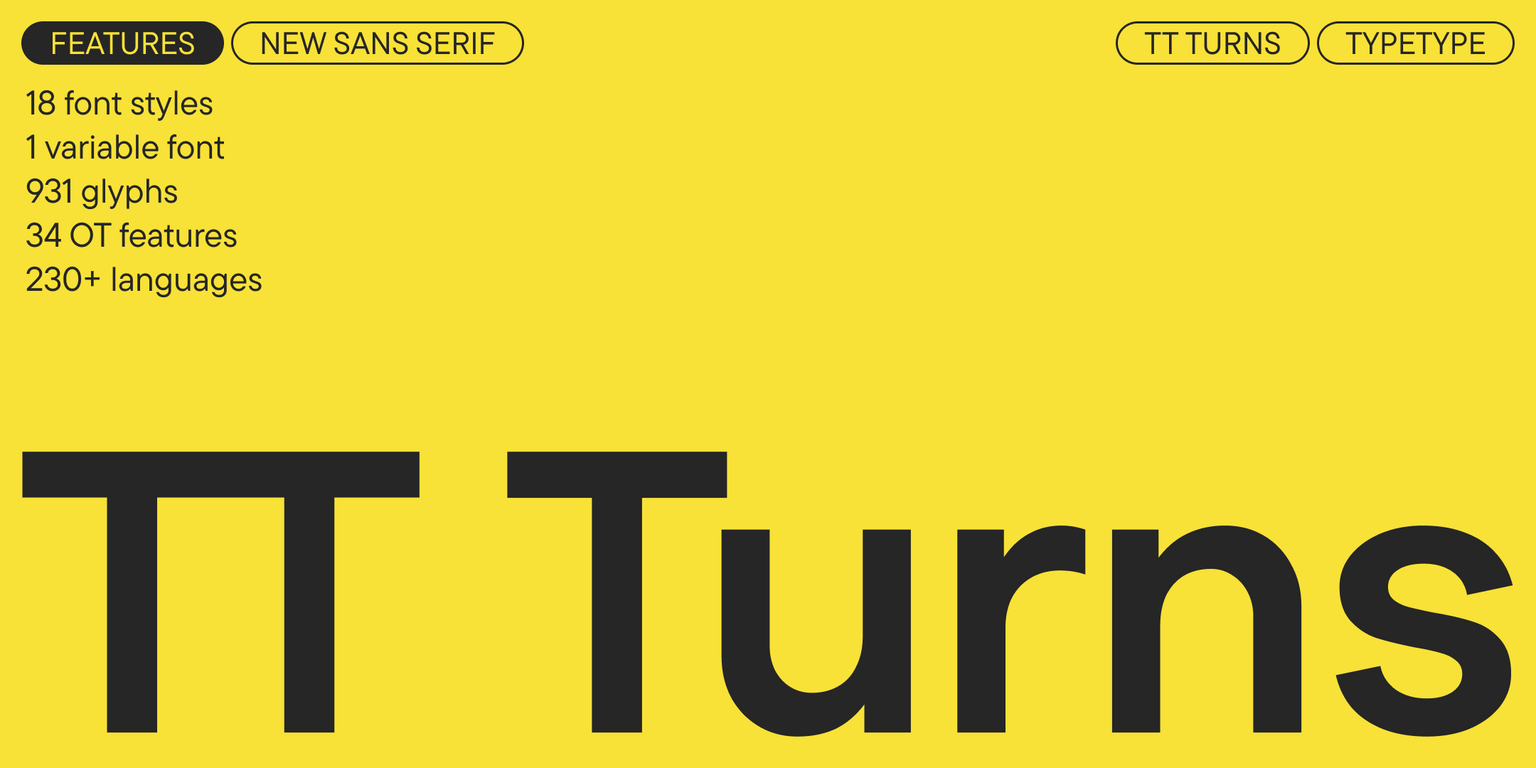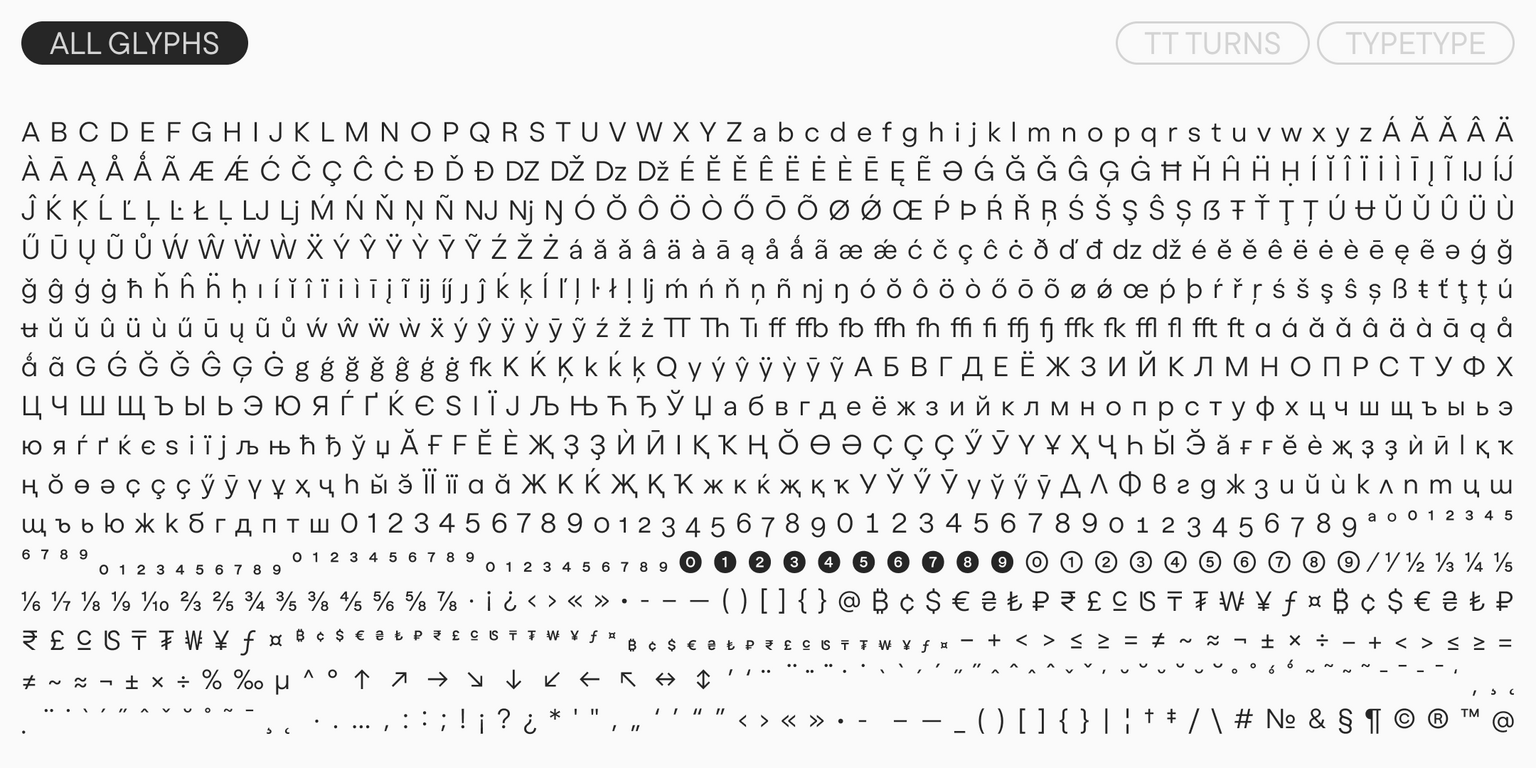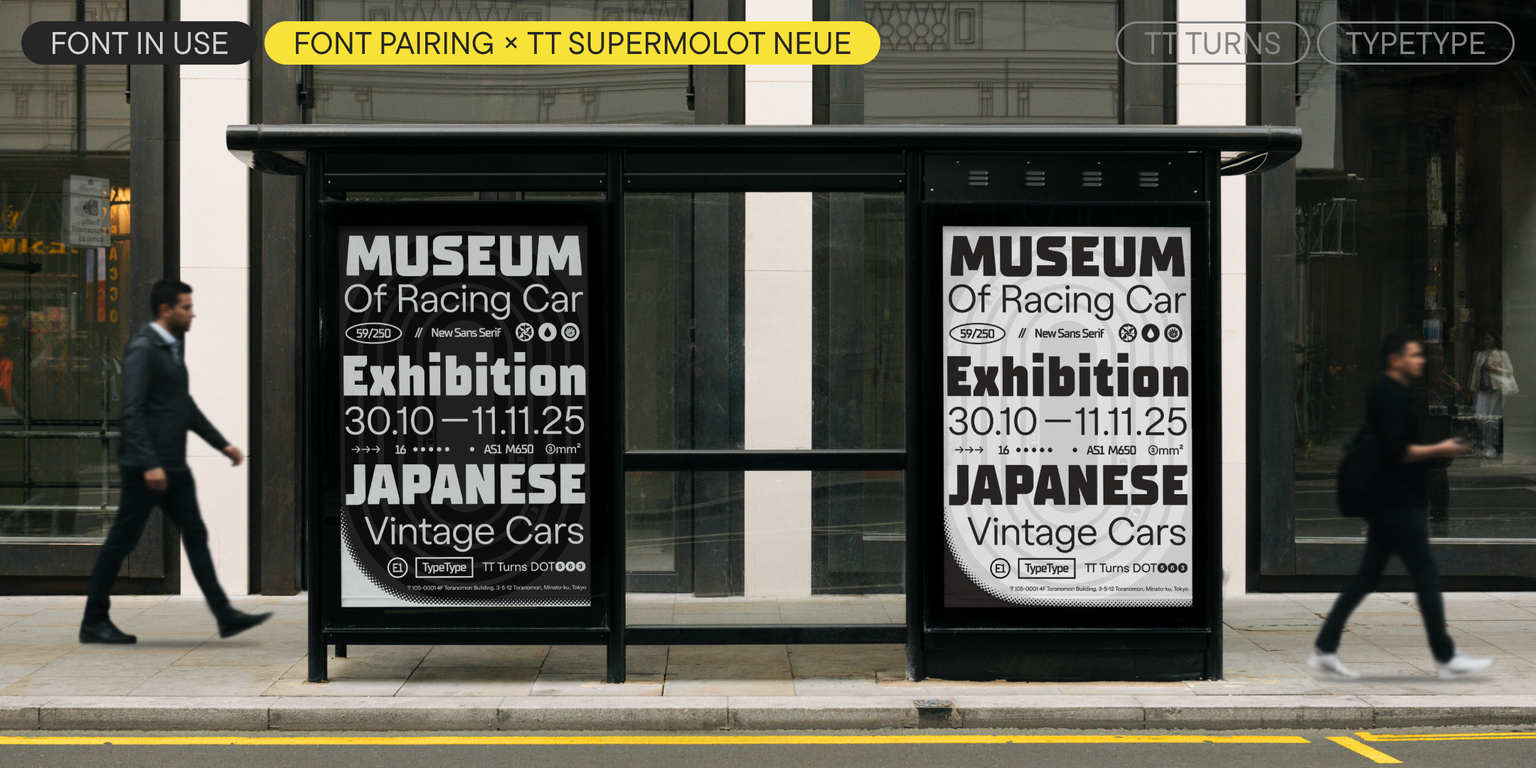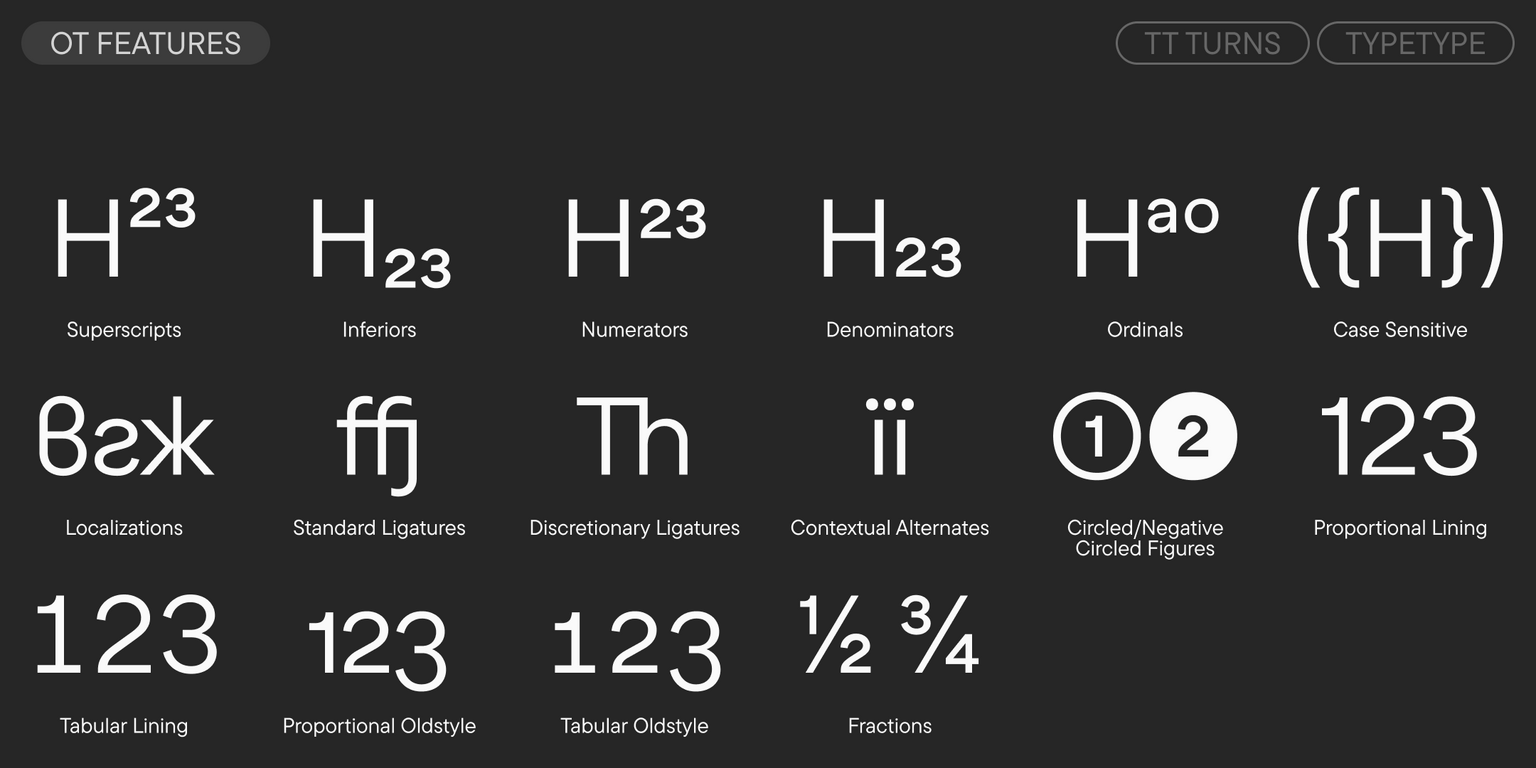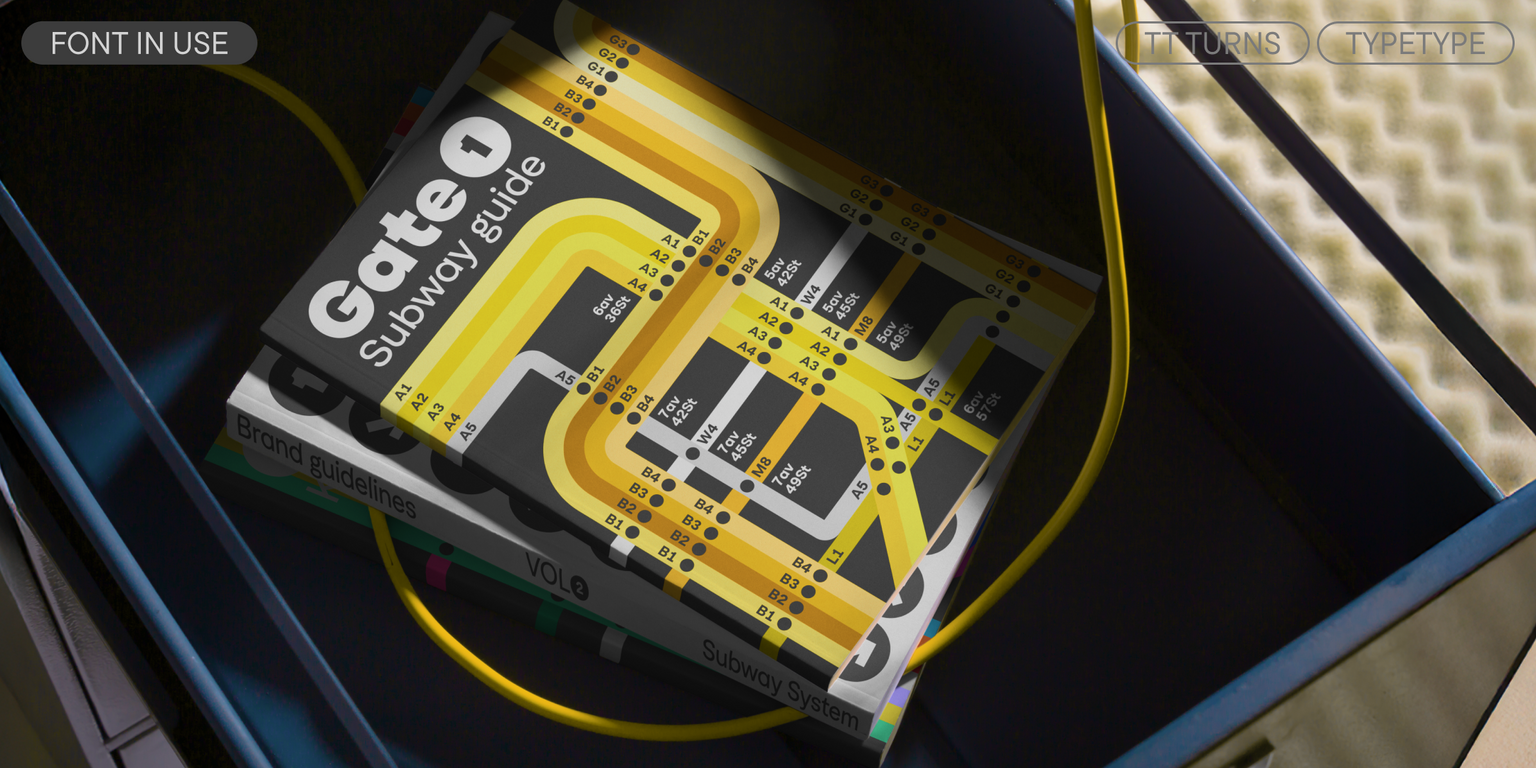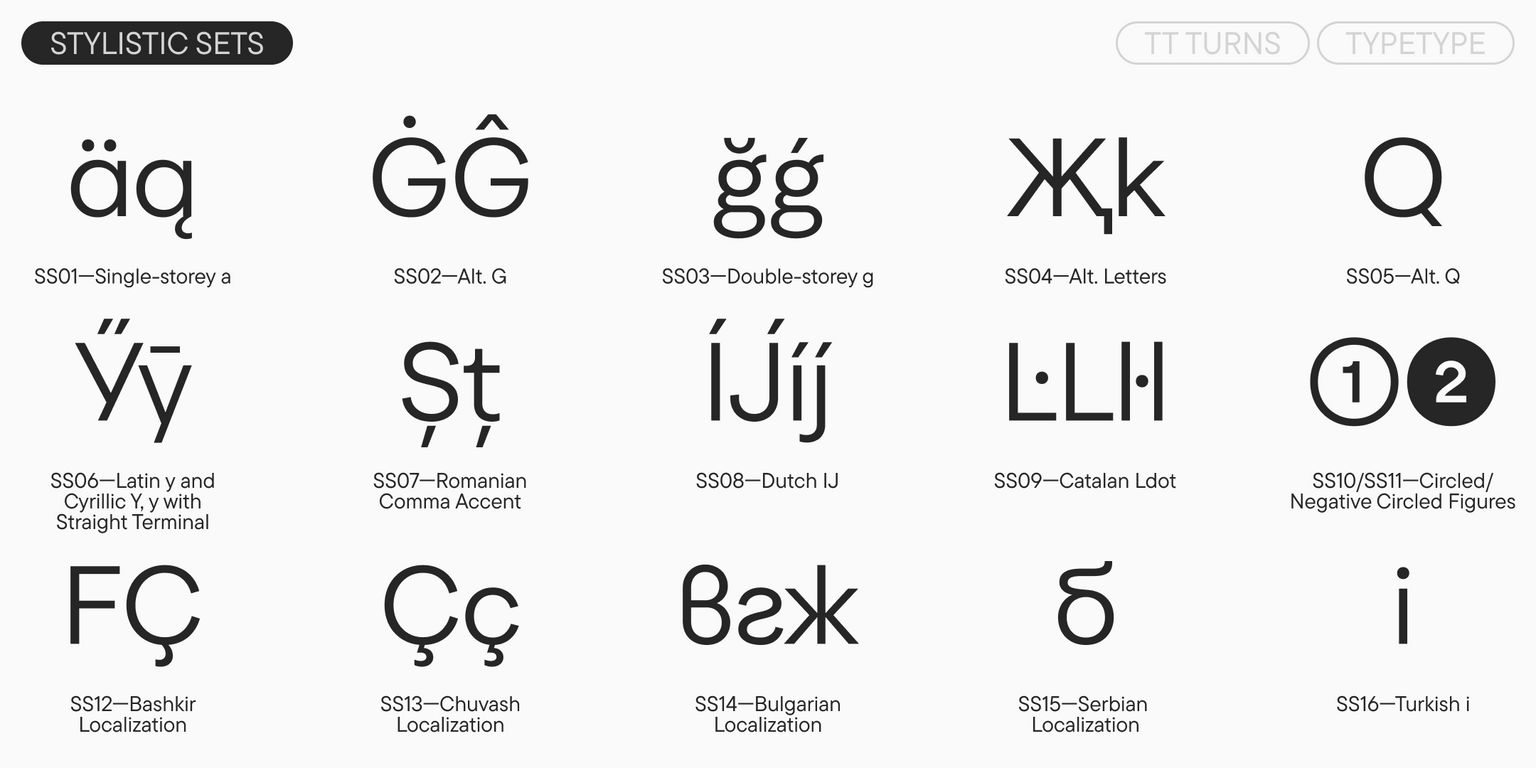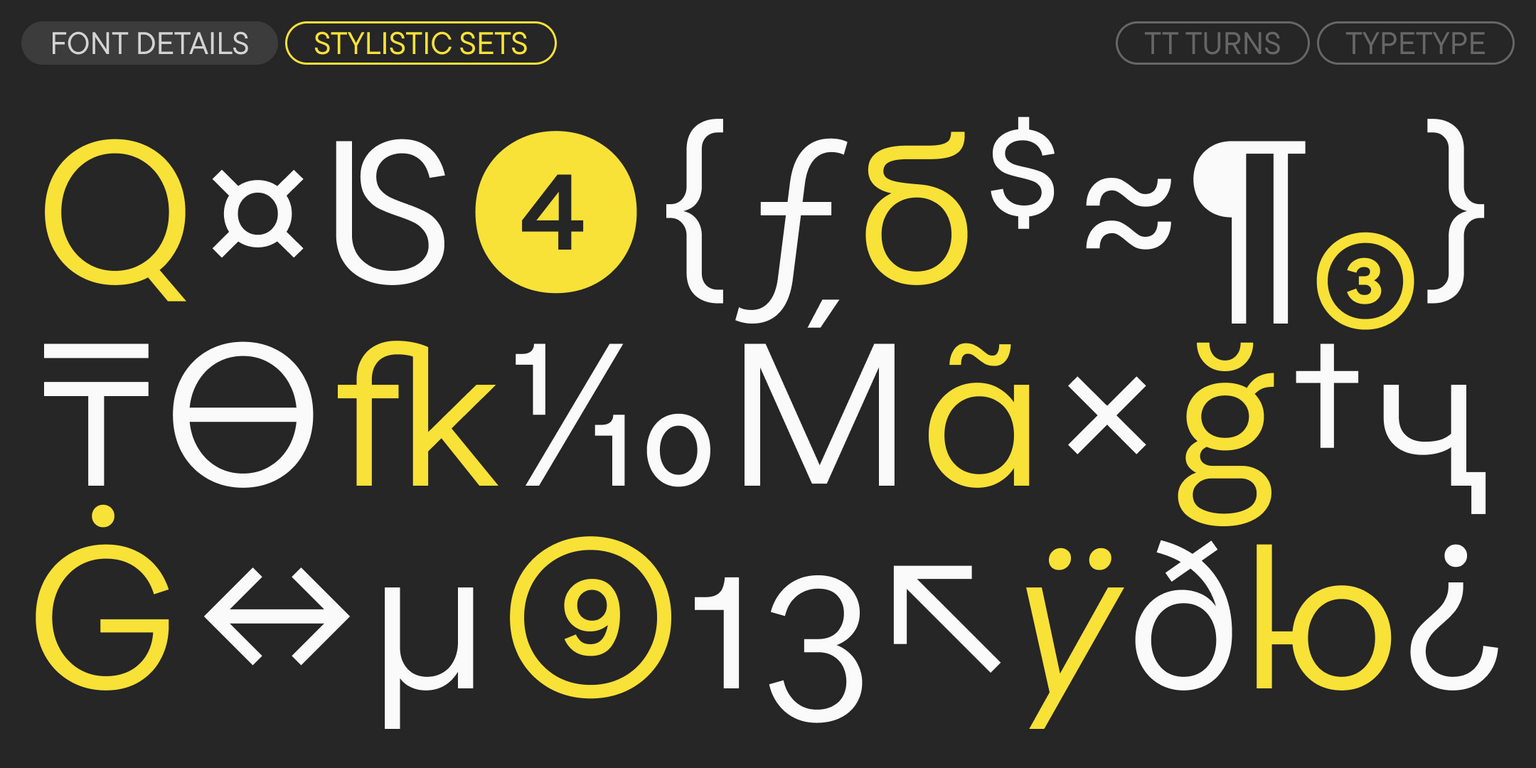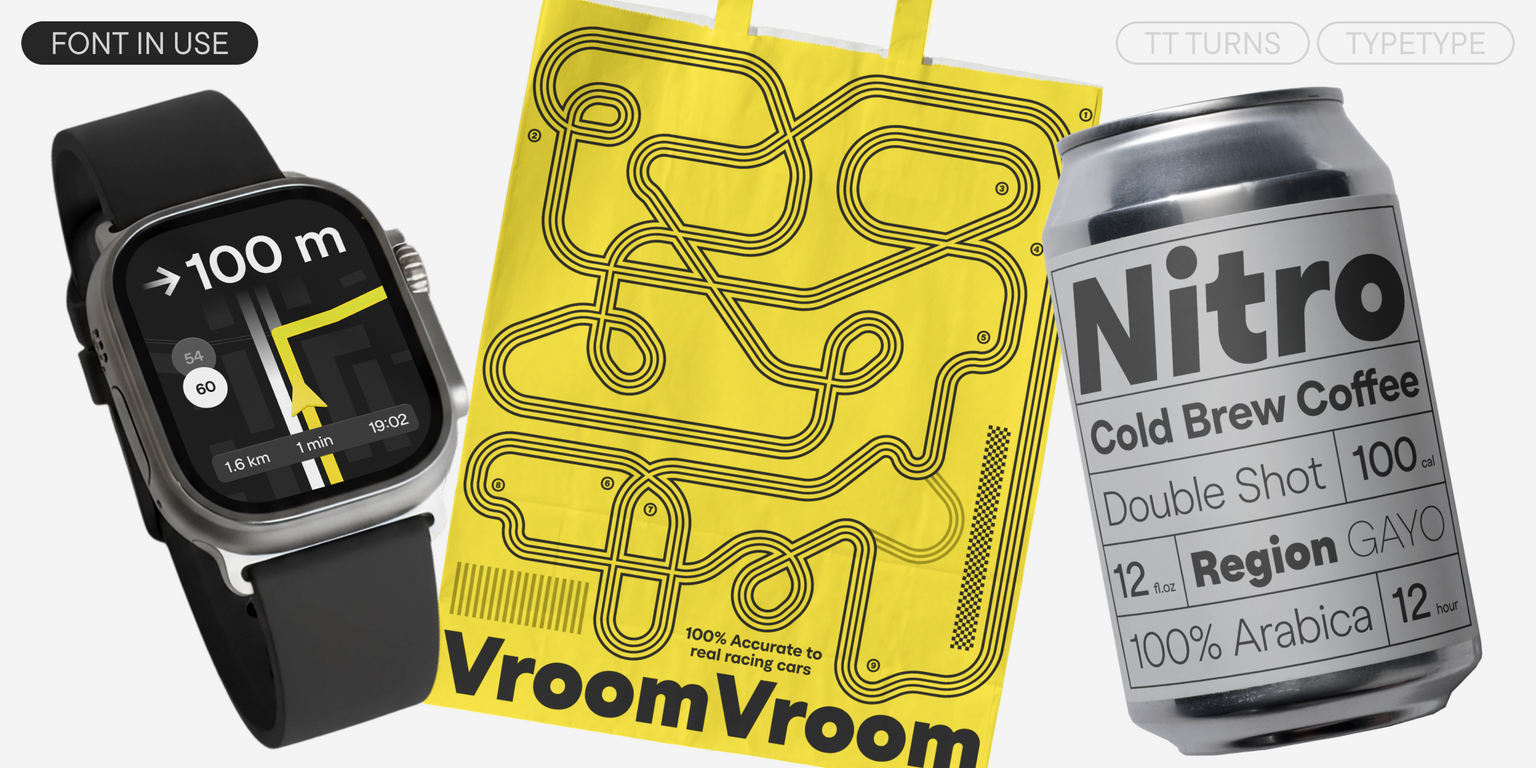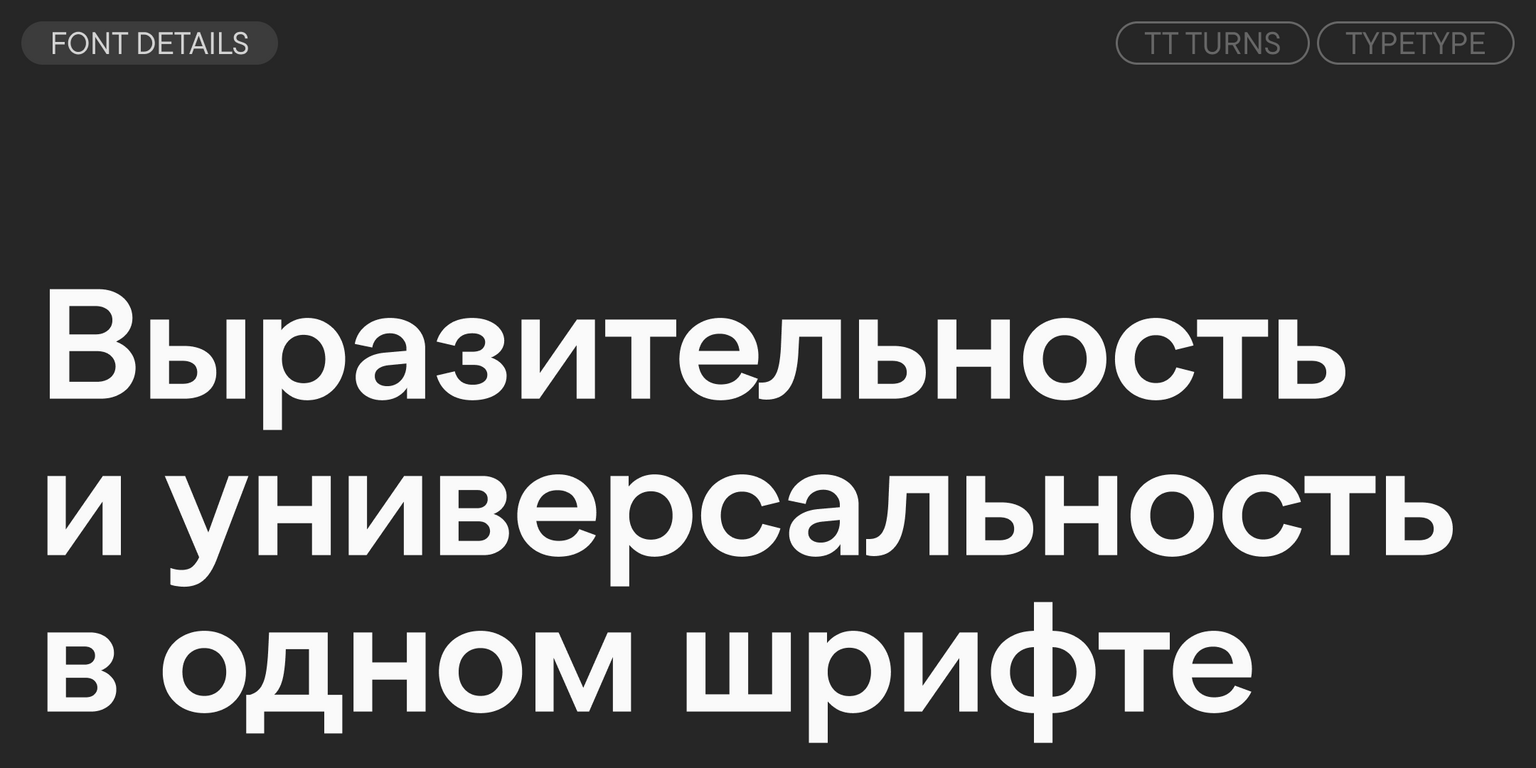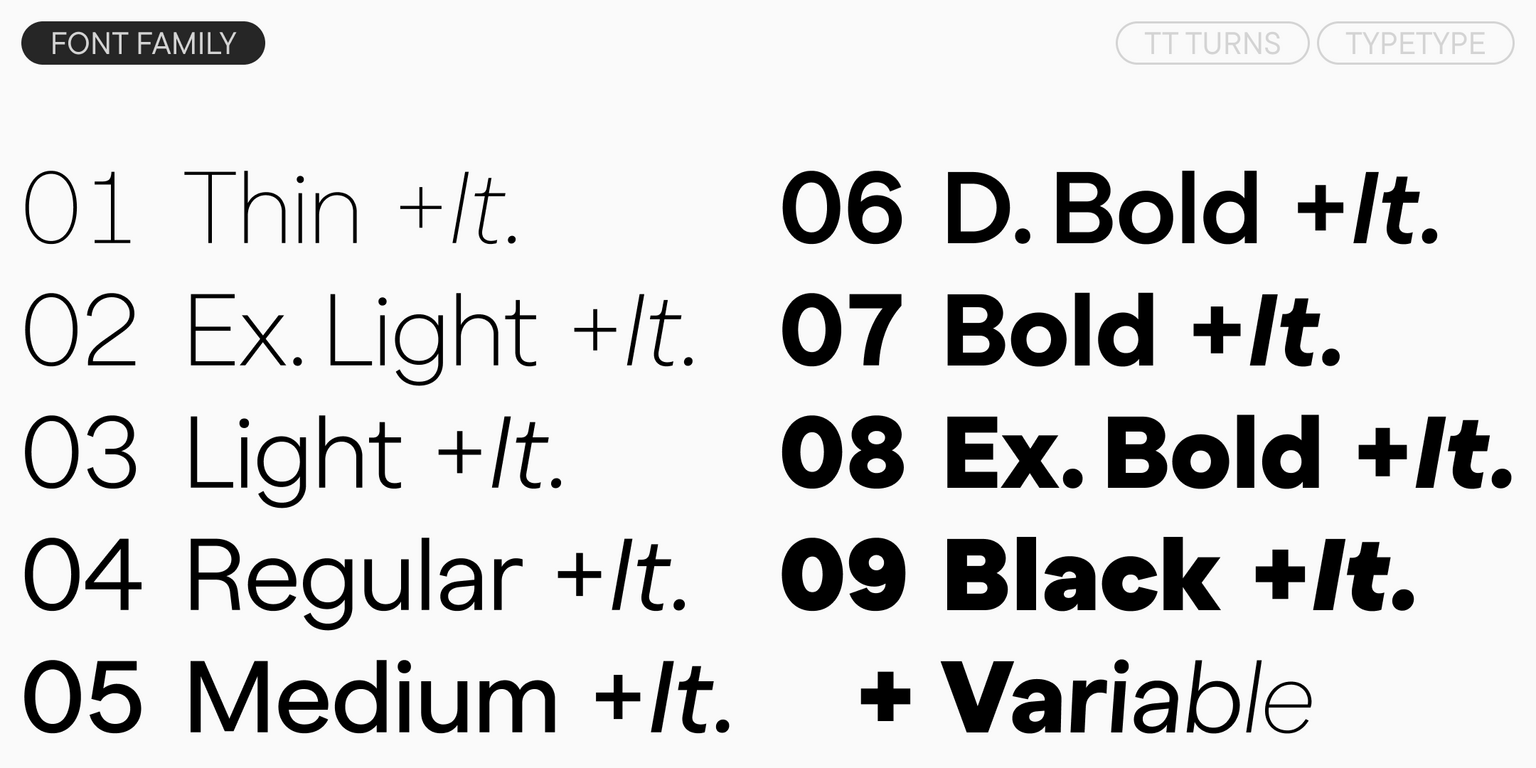
TT Turns
TT Turns — ТТ Тернс
Произносится «ТТ Тернс». «Turns» — производное слово от turn, в переводе с английского «поворот». Буквы «TT» являются аббревиатурой названия компании.
TT Turns — яркий геометрический гротеск с выразительными элементами. Это универсальный шрифт, который отлично работает в текстовом наборе, при этом в крупных размерах становится акцидентным.
Новое прочтение симбиоза геометричности и гуманистичности
Основной идеей шрифтового семейства TT Turns стало создание новой универсальной гарнитуры, которую можно одинаково эффективно применять практически в любой сфере. Шрифт тщательно выверен и представляет собой строгий расчёт сбалансированных пропорций, что позволяет рассматривать его как достойную альтернативу классическим гротескам. Характер шрифта сохраняет нейтральность, оставаясь при этом современным. В процессе работы над рисунком в шрифт были добавлены уникальные элементы: особые терминалы в буквах «a» и «g», а также специфичные формы, характерные для ширококонечного пера в кириллических «Дд» и «Лл». Эти детали придают гарнитуре лёгкую акцидентность — около 5% — что становится её ключевой особенностью и помогает выделиться среди других шрифтов. Мы также включили в шрифт множество OpenType фич, значительно расширяющих его возможности. Доступны шесть стилистических сетов (наборов), которые заменяют отдельные знаки на альтернативные формы: первый набор меняет «а» на одночастную форму, второй придает «G» геометричность, третий заменяет «g» на двухчастный вариант, четвертый корректирует соединение диагоналей в «Kk», пятый изменяет хвост «Q», а шестой делает хвост «y» прямым.
В комплекте шрифта 19 начертаний: 9 прямых, 9 наклонных и 1 вариативный шрифт
Мы добавили в шрифт 5% дружелюбности и уникальности
О гарнитуре TT Turns
Встречайте новый TT Turns — базовый и яркий одновременно!
TT Turns — геометрический гротеск с акцентными круглыми знаками и выразительными нависающими элементами. Это универсальный шрифт, который лаконично выглядит и отлично читается в маленьком размере, при этом в крупных кеглях становится акцидентным и проявляет свой характер на максимум. Он энергичный, сильный и динамичный — особенно отчётливо это проявляется в наклонных начертаниях.
В «Kk» и «Жж» диагонали подходят к стему под крутым углом, за счёт чего образуется яркий треугольник белого пространства. Это добавляет рисунку остроты. Также среди характерных деталей — крутые окончания у «Ss», «Cc», «a», «Ээ», «Зз», выразительная нога у «R», подчёркнуто выступающие штрихи в левых частях «Лл» и «Дд».
Ещё больше акцидентности шрифту можно придать с помощью ярких стилистических сетов. Так, «а» можно поменять с двухчастной на одночастную, «g» — с одночастной на двухчастную, форму «G» заменить на круглую, изменить графемы «Жж», «Кк», «Kk», преобразовать форму хвоста «Q». А если вы хотите, напротив, «успокоить» набор, на помощь придёт сет с более строгими формами хвостов кириллической «Уу» и латинской «y». Также в шрифте есть лигатуры, множество OpenType фич, значительно расширяющих его возможности, и вариативное начертание, меняющееся по осям жирности и наклона.
TT Turns подойдёт для множества различных задач: от использования в текстовом наборе, в вебе и приложениях до брендинга и оформления упаковки. Его можно одинаково эффективно применять практически в любой сфере.
В TT Turns входит:
• 19 начертаний: 9 прямых, 9 наклонных и 1 вариативный шрифт;
• 931 знак в каждом начертании;
• 34 OpenType фичи;